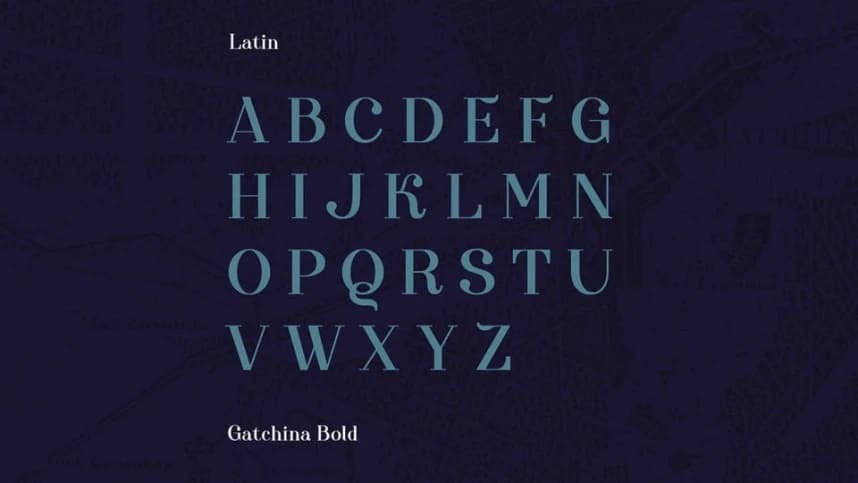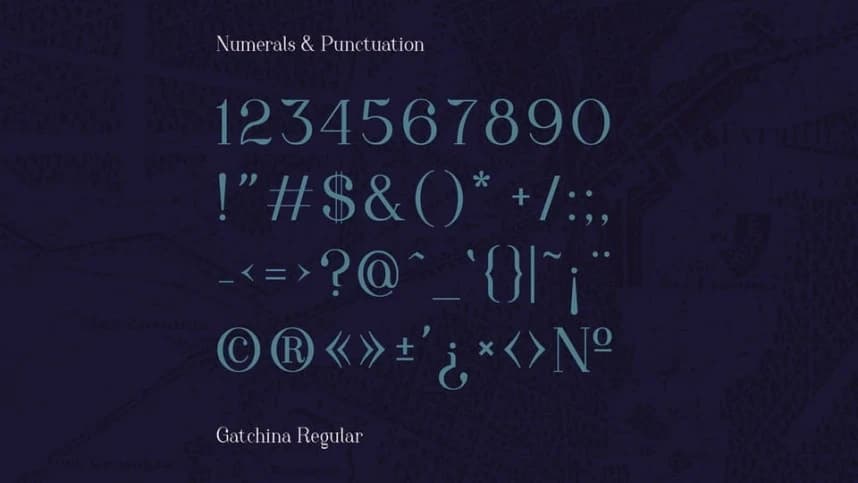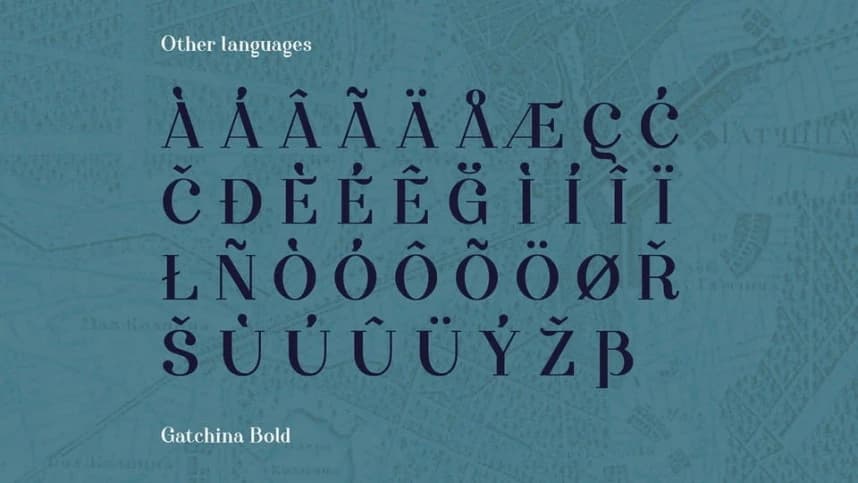
Gatchina Font
Gatchina Font, zarif bir serif yazı tipi olup sakin bir sofistike ve zarafet duygusu yaratır. Şık oranları ve ince kontrastları ona klasik bir roman başlığı hissi ya da eski bir saray kapısının yazıtı etkisi verir.
Gatchina Font, zarafet ve inceliğin sakin bir hissine sahip gelişmiş bir serif yazı tipidir. Şık orantıları ve ince kontrastları ona klasik bir roman başlığı hissi veya eski bir saray kapısının yazısı izlenimi verir.